Voici donc quelques nouvelles de ce qui se passe, en ce moment, dans mon petit atelier…
Calligraphie, lettering et illustration
Vous vous rappelez mes bonnes résolutions (ou plutôt mes objectifs de début d’année) ? Bon et bien je m’y tiens fermement, même si le dessin et l’illustration ont pas mal pris le pas sur la calligraphie ces derniers temps.
Le fait de participer au MATS Bootcamp en est la principale raison, puisque tout le travail consiste justement à faire… des illustrations, sur des thèmes imposés.
J’ai bien sûr inclus du lettrage dessiné ou calligraphié (on ne se refait pas), mon idée étant de marier les deux le plus possible.
Autour de la plume palette
Je confirme, la plume palette est vraiment un chouette outil pour le lettrage. Il me reste pas mal de recherches à faire pour affiner le style et travailler les compositions, mais c’est bien pratique pour des petites citations.
J’ai travaillé soit des cursives un peu naives (enfantines), soit des capitales aux accents rétro ou carrément Art Déco.
Dans un style plus Art déco et rétro:
Si la plume palette vous intéresse, je vous invite à consulter l’article que j’avais consacré à cet instrument il y a quelques semaine, ainsi que le petit DIY pour des cartes Vintages.
Lettering et illustration
Au gré de mes différents dessins, je teste le lettrage. Un peu difficile car c’est assez rigoureux au niveau des tailles, de l’espacement, de la netteté, mais comme c’est utilisé dans des illustrations, je me permets d’être moins rigoriste. Cela donne un effet un peu plus dansant ou amusant que si les lettres étaient absolument parfaites.
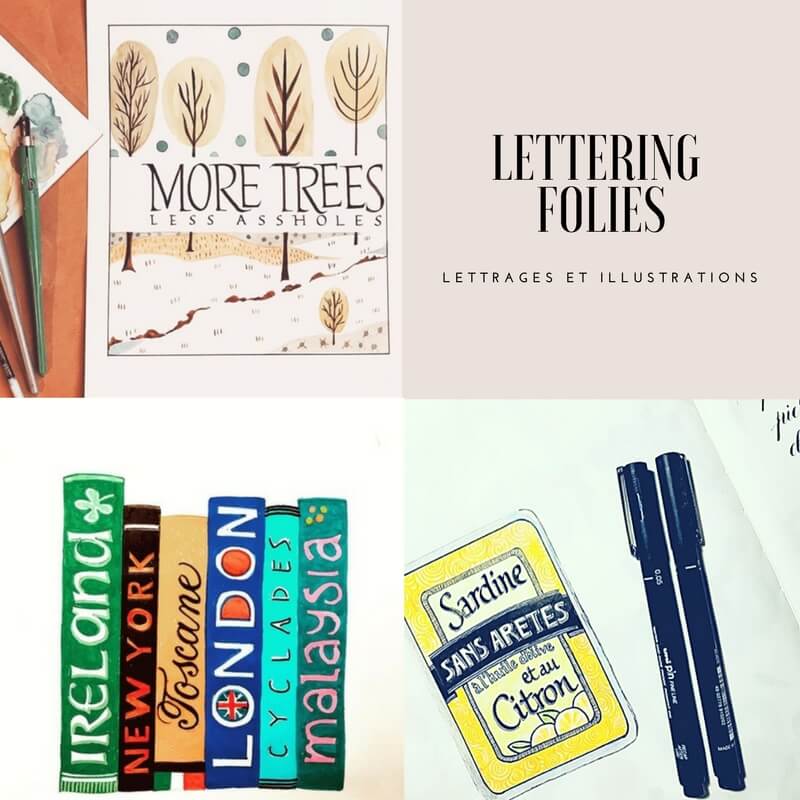
Peu à peu tout cela prend forme, et me force aussi à travailler « proprement », puisque je partage beaucoup sur Instagram.
Autour du Thé
Le thème de février qui était assigné pour le MATSBOOTCAMP était le thé. J’ai beaucoup aimé ce thème, qui offre énormément de pistes créatives et ludiques : mugs et tasses, boites à thé, sachets de thé, plantes, bien-être, culture, traditions, poèmes etc.
Je partagerai prochainement plus de réalisations sur ce thème, mais si un jour vous êtes en panne, songez au thé et à son univers, c’est très inspirant; J’ai rassemblé pas mal d’idées sur un petit tableau Pinterest, si cela vous intéresse.
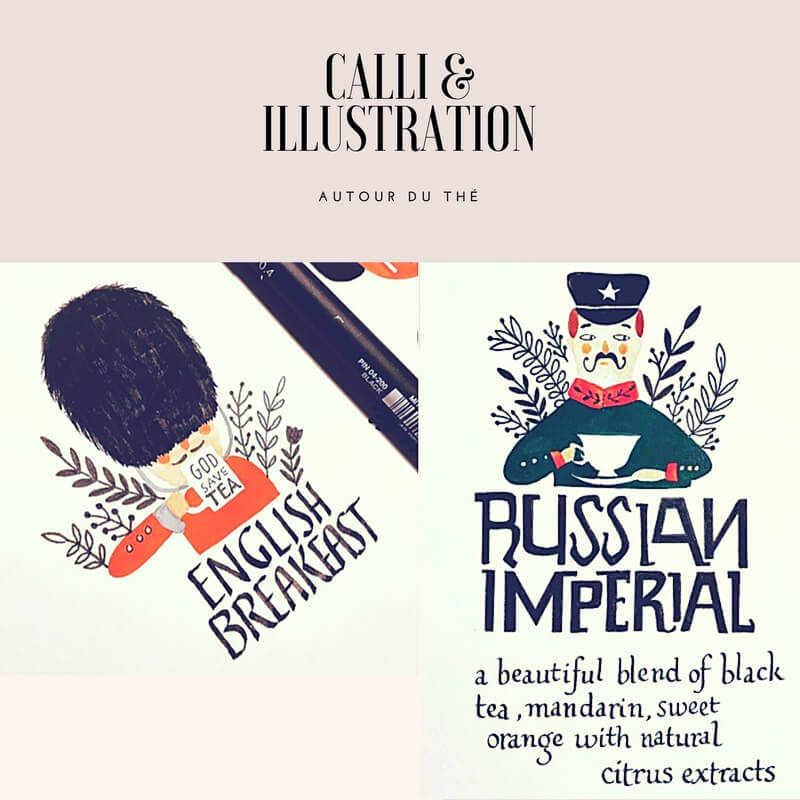
Voilà la petite actualité du mois de mars, en attendant que les beaux jours reviennent vraiment et nous transportent dans le vert, les fleurs…
Pour finir une petite citation que j’aime beaucoup :
La créativité, c’est inventer, expérimenter, grandir, prendre des risques, briser les règles, faire des erreurs et s’amuser – Mary Lou Cook